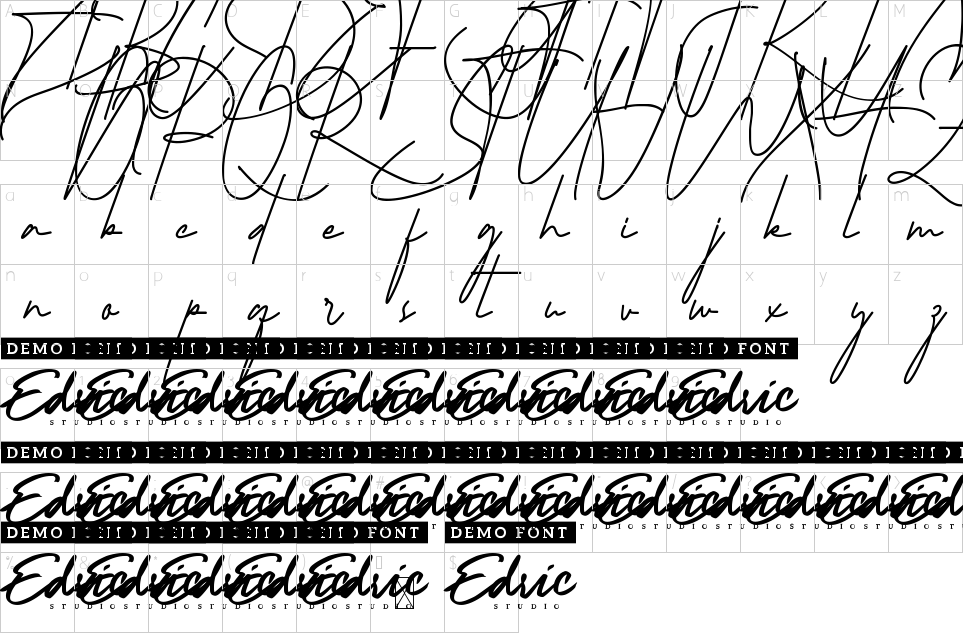
A fonte ‘Salisbury’ é uma opção perfeita para qualquer designer que busca uma fonte moderna e fácil de ler para projetos digitais. Desenvolvida pela EdricStudio, esta fonte vem para proporcionar uma experiência visual consistente em sites, aplicativos e materiais impressos. Com uma aparência elegante e versátil, Salisbury pode ser utilizada em títulos e sub-títulos, oferecendo um contraste suave que pode realçar o texto sem tornar o design exagerado. Se você é um designer gráfico que busca uma fonte gratuita para projetos profissionais ou pessoais, a ‘Salisbury Font’ é uma ótima escolha. Desde quando foi lançada, mais de 1.592 usuários já aproveitaram suas facilidades. Se você está pronto para experimentar a legibilidade e o design elegante desta fonte, não perca mais tempo, o ‘Salisbury Font’ está esperando para ser adicionada ao seu arsenal de recursos de design.